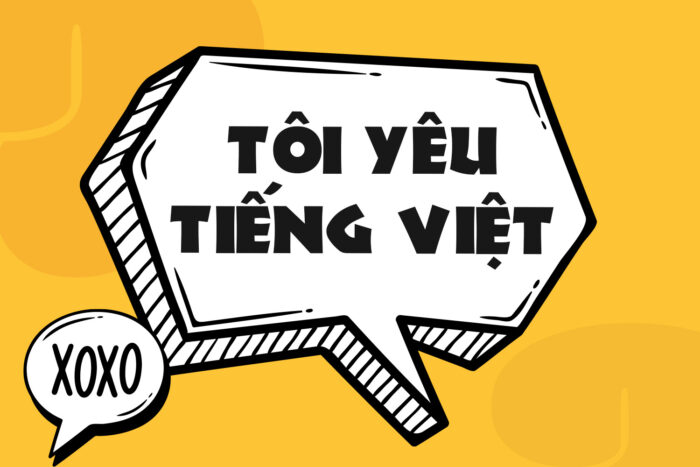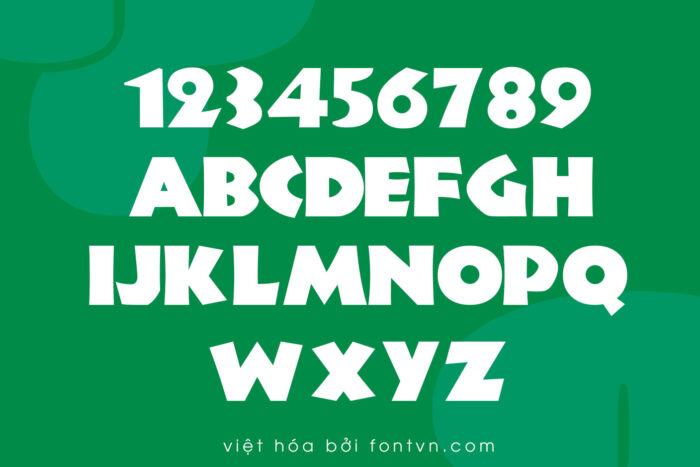
DVN Jungle Fever Việt hóa – Font chữ Comic phù hợp cho truyện thanh và thiết kế năng động
“Jungle Fever” là một font chữ mang phong cách comic độc đáo với các đường nét cong và góc nhọn độc đáo. Kiểu chữ này có sự pha trộn giữa tính vui tươi và sự mạnh mẽ, thể hiện qua các ký tự có độ dày đều, kết hợp với những nét uốn lượn tự nhiên. Điều này tạo nên cảm giác hoang dã, phù hợp với các chủ đề liên quan đến thiên nhiên, phiêu lưu, và sự sáng tạo.
Các ký tự trong “Jungle Fever” có xu hướng ngả nhẹ, tạo ra một cảm giác chuyển động và linh hoạt, giúp nó nổi bật trong các thiết kế cần sự thu hút. Font chữ này lý tưởng cho việc sử dụng trong các poster, bìa sách, trò chơi điện tử, và các dự án thiết kế cần sự năng động và tính giải trí. “Jungle Fever” không chỉ là một lựa chọn thú vị mà còn đem lại sự sinh động và cá tính cho mọi tác phẩm.